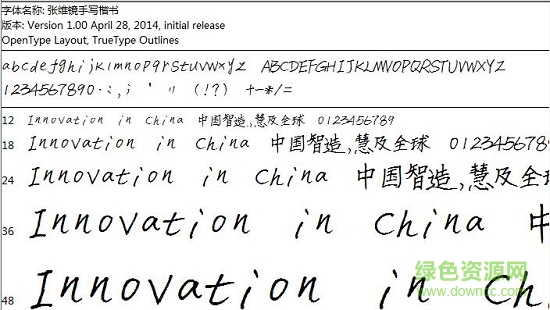
張維鏡手寫字體
張維鏡手寫楷書是一款鋼筆手寫書法字體,這款字每一個字都非常的工整,每一筆一劃都能看出作者創(chuàng)作時的用心,有需要的朋友歡迎下載使用!
張維鏡手寫楷書簡介
張維鏡手寫楷書是一款根據(jù)手寫字體打造而來的楷體字體,這款字體完美的歡迎了作者的手寫書法,每一個字都能輕松的看出作者的用筆習(xí)慣,適合有需要經(jīng)常用到各種字體進行創(chuàng)作的朋友!
張維鏡手寫楷書